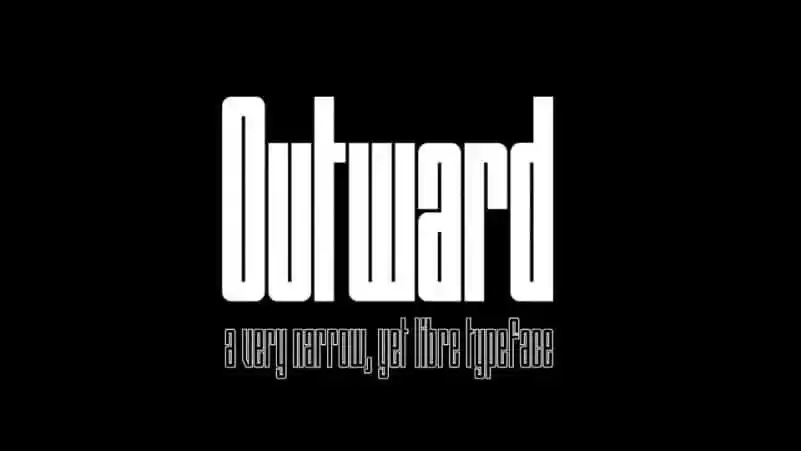
A fonte Outward Display é ideal para criar visuais chamativos e criativos, especialmente em aplicações onde a atenção deve ser focalizada. Desenvolvida com uma grande altura máxima, ela oferece um tipo condensado extremamente estreito que se destaca como uma excelente opção para aplicações digitais e impressos. Esta fonte é uma fonte de tipo livre, projetada por Raoul Audouin na 99designs. Com três diferentes cortes: Block (regular), Round (italic) e Borders (bold), a Outward Display está equipada com uma coleção completa de pares de kerning, desenhados para minimizar o espaçamento entre as letras. Isto torna a fonte ainda mais atraente e permite que os designers criem layouts aparentemente sinuosos, mesmo em tipos estreitos. A Outward Display é uma excelente escolha para projetos que exigem um tipo bem condensado e concentrado, tanto no design impresso quanto na web. Ela suporta uma grande gama de caracteres latino-cyrillics, garantindo que seja compatível com múltiplos idiomas modernos. Com sua atenção direcionada para o público que busca um tipo visualmente impactante, a Outward Display oferece uma opção perfeita para designers buscando um tipo capaz de destacar em qualquer plataforma.